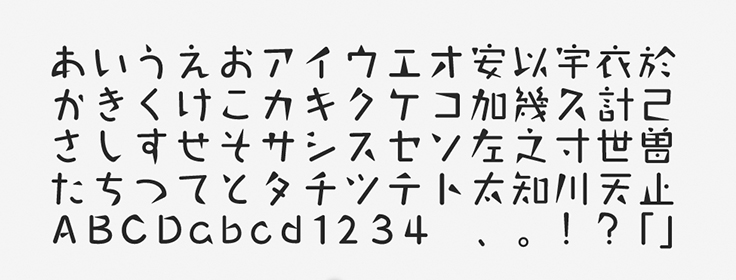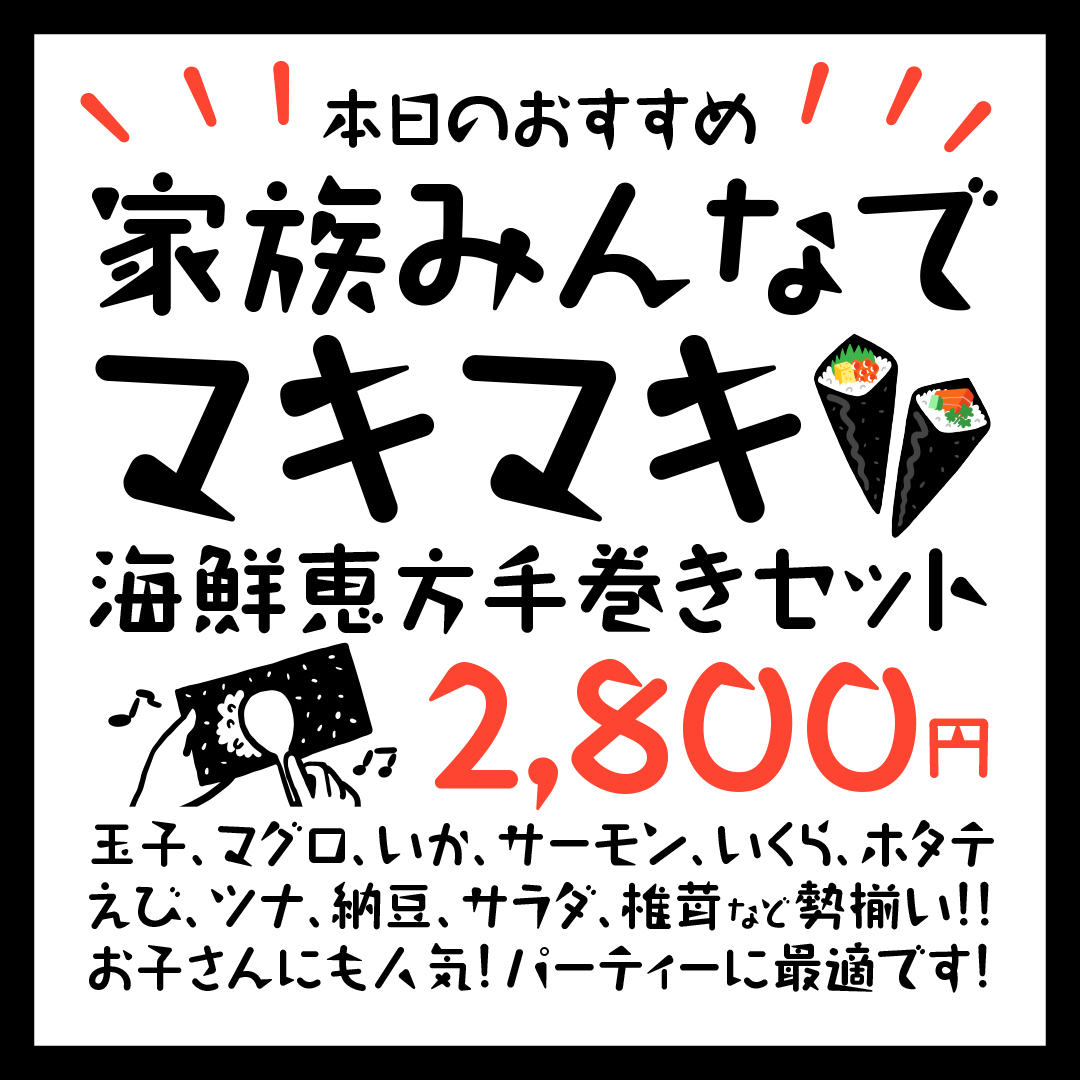
「タカリズム」について
タカハンドでも有名な、たかデザインプロダクション(高原新一書体デザイン室)が手掛ける「タカ書体」の1つで、2013年にモリサワでの提供が開始されました。広告の分野をはじめ、ロゴタイトルや見出しやディスプレイなど、幅広い場面で楽しいフォントとして活躍しています。
「タカリズム」の特徴
文字のエレメントに丸や三角が取り入れられていることが大きな特徴で、「リズム」の名前の通りに弾むような躍動感が生み出されています。線幅や画線の角度も文字ごとに自由にデザインされており、普通に文字を組むだけでもワクワクするような動きを表現することが可能です。
リズミカルで躍動感がありながらも、雑な印象は与えません。その理由は正方形を意識した安定感のある骨格で、素朴な楽しさとともにしっかりと文字として読ませるデザインを実現できます。
タカリズムは、丸や三角などのエレメントが可愛いデザインです。作例は手巻き寿司パーティーを提案するスーパーのPOPなので、楽しそうな様子をイメージできるようにタカリズムを使いました。にぎやかな雰囲気も演出しやすいフォントです。